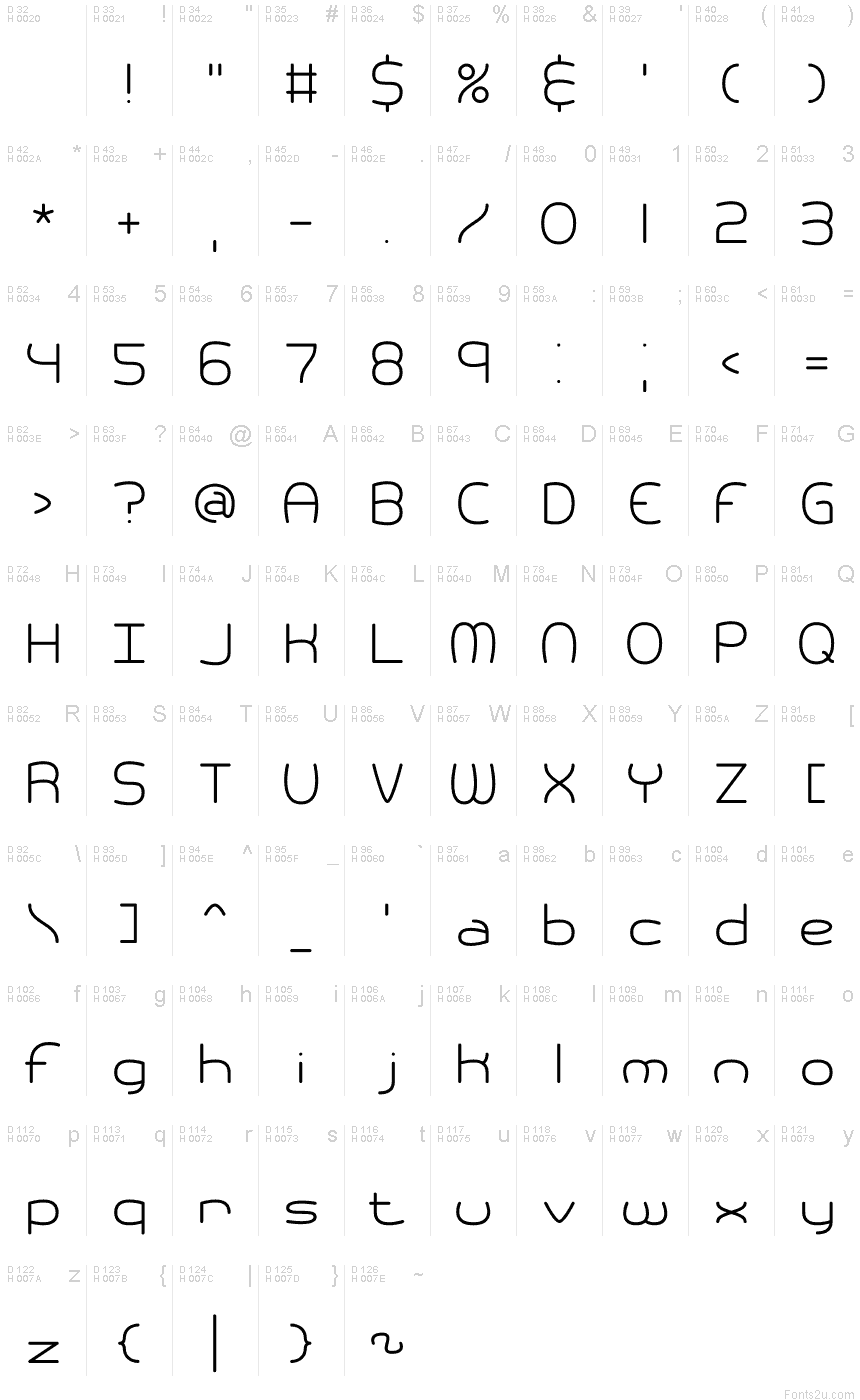
Pneumatics BRK od ÆNIGMA Fonts to darmowy, geometryczny krój pisma typu display, wyróżniający się zaokrągleniami i czystym, niemal pneumatycznym przepływem. Litery płynnie przechodzą jedna w drugą dzięki miękkim liniom o stałej grubości, szerokim łukom i otwartym formom, co nadaje całości lekki, nowoczesny i nieco retro-futurystyczny charakter.
Świetnie sprawdzi się w identyfikacjach wizualnych, projektach opakowań, nagłówkach plakatów, okładkach płyt czy planszach tytułowych – wszędzie tam, gdzie darmowy font ma nadać projektowi płynny, techniczny klimat, nie stając się przy tym zbyt chłodnym w odbiorze. Użyj go, jeśli chcesz, aby krótkie nazwy, napisy na okładkach czy logotypy były jednocześnie lekkie i mechaniczne; powtarzające się koliste kształty nadają nawet prostemu tekstowi ciągły, opływowy rytm.
Pneumatics BRK